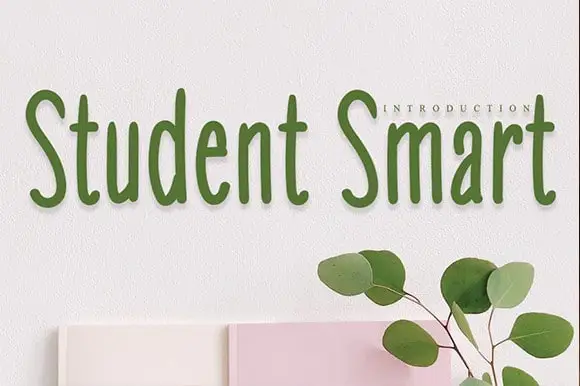
Student Smart Font – Download Grátis
A Student Smart Font é uma elegante escolha para os designers aventureiros. Suas linhas arredondadas e detalhes finos oferecem um visual sofisticado ideal para expressar seu projeto de maneira única, sejam eles logos de redes sociais, embalagens de produtos ou até mesmo post-its criativos. Esta fonte serif é perfeita para qualquer aplicação que precise de uma mão-dura charmosa e autêntica. Composta por 410 caracteres, a Student Smart Font tem um conjunto completo de opções: do padrão simples aos detalhes mais elaborados. Este é o tipo de font que vai dar aos seus projetos uma dose extra de sofisticação. Seja para criar um post impressionante nas redes sociais ou para personalizar suas embalagens, esta fonte serif certamente será a escolha perfeita. Ela é versátil e pronta para qualquer formato do seu projeto — seja ele wall-display, invitações, artefatos de marca, logotipos, ou até mesmo como uma mão-dura na sua próxima fotografia. Agora, se você está procurando por um tipo de letra que pode dar à sua identidade visual o toque definitivo com a mesma elegância e sofisticação dos anos 80 e 90 sem perder a modernidade do design atual, a Student Smart Font é a fonte para você. Ela foi criada pensando em designers apaixonados por criar trabalhos excepcionais que combinam funcionalidade e beleza.